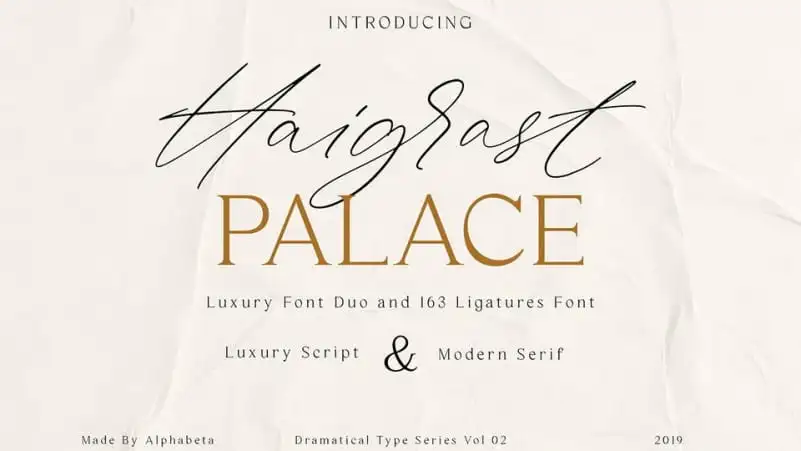
Haigrast Font Duo
Haigrast Font Duo é uma paixante perfeitamente combinada entre a script moderna e o tipo serif, inspirada na nova concepção de caligrafia moderna. Este conjunto de fontes está disponível gratuitamente para todos os designers que procuram dar um toque exclusivo às suas criações digitais. A combinação de uma tipografia luxuosa e um tipo serif moderno é perfeita para criar designs dramáticos e imponentes. Esta paixante traz um toque dramático, proporcionando qualidade única aos seus projetos. Ela também oferece um toque contemporâneo que renova a estética tipográfica, tornando-a mais simples e prática na hora de simplificar o design digital. Seja para criar headlines impactantes ou textos detalhados, Haigrast Font Duo garante que qualquer projeto esteja impecável e moderno, fazendo dela uma opção ideal para designers em busca de um desempenho excepcional em seu trabalho.